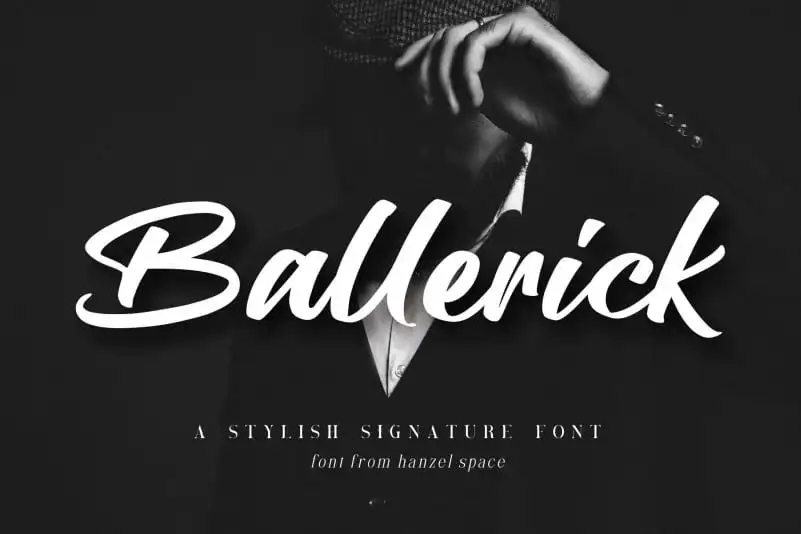
A Ballerick Brush Font é uma elegante tipografia script criada com amor por Hanzel Studio, designer do 99designs. Esta fonte traz uma sensação natural e autêntica de escrita a mão, ideal para seus projetos que incluem Headline, roupas, convites, marcações, casamentos, logotipos, arte livre, publicações, panfletos e outros trabalhos de design. Com um toque único da escrita a mão, Ballerick se ajustará perfeitamente para qualquer necessidade de estilo que você possa encontrar no seu próximo projeto visual, garantindo a originalidade e sofisticação que sua marca merece.